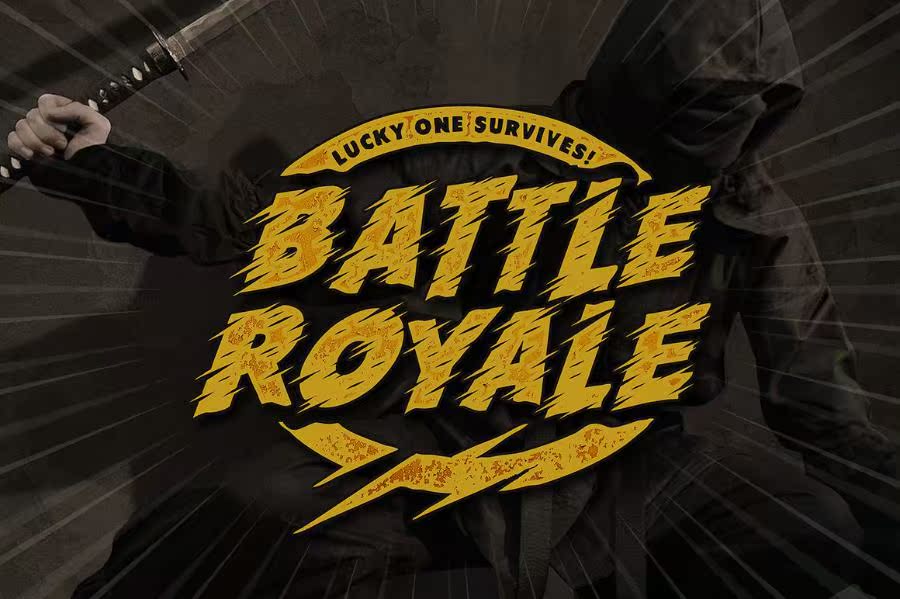
Run Typeface Free演示版是一款引人注目的字体的试用版!这种倾斜的SAN是一种。所有的能量和耐力都来自A-Z。一个完美的构建为您的响亮的设计项目。现在,只需应用很少的效果,您就可以将演示文稿提升到下一个级别!即使是纯色,也要跑!字体刺穿了你的眼睛。您可以将其用作YouTube缩略图、博客标题、品牌标识、徽标设计、标签和海报。